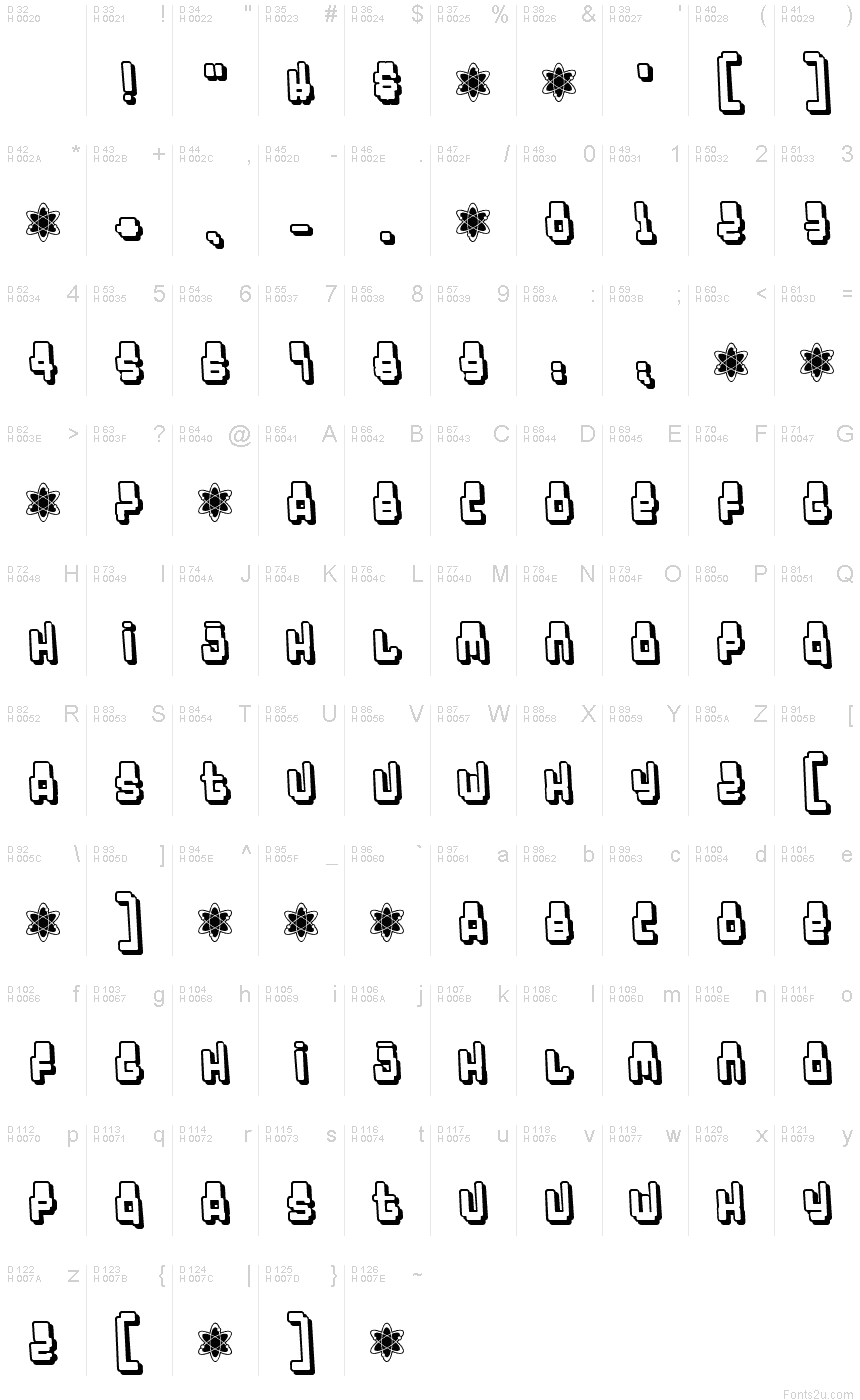
Oddessey 7000 من Font"a"licious Fonts هو خط عرض رقمي ثلاثي الأبعاد مجاني يبدو وكأنه خرج للتو من أجهزة الألعاب القديمة (أركيد). الحروف الضخمة ذات الشكل المربع والحواف المتدرجة التي تشبه البكسل تضفي طابع الخيال العلمي المرح، بينما تمنح الأشكال الجريئة والقائمة ثقلاً وصلابة على الشاشة. وهم الأبعاد الثلاثية الدقيق يعطي كل حرف ملمساً بلاستيكياً، وكأنها خراطيش ألعاب لامعة مصطفة في صف واحد.
باستخدام Oddessey 7000، يمكنك تعزيز مشاعر الحنين إلى الماضي في عناوين الألعاب، وملصقات فعاليات الخيال العلمي، والعلامات التجارية التكنولوجية ذات الطابع القديم، وصور مصغرة لموقع يوتيوب، والملصقات والهدايا الترويجية. يتألق هذا الخط المجاني عند استخدامه بحجم كبير مع مسافات ضيقة بين الحروف، مما يسمح للخطوط العريضة بأن تتداخل كقطع في لعبة منصات كلاسيكية. بالنسبة للنصوص التوضيحية، قم بإقرانه بخط sans serif هندسي نظيف بوزن خفيف للحفاظ على سهولة القراءة دون فقدان تلك السحر الرقمي الضخم.